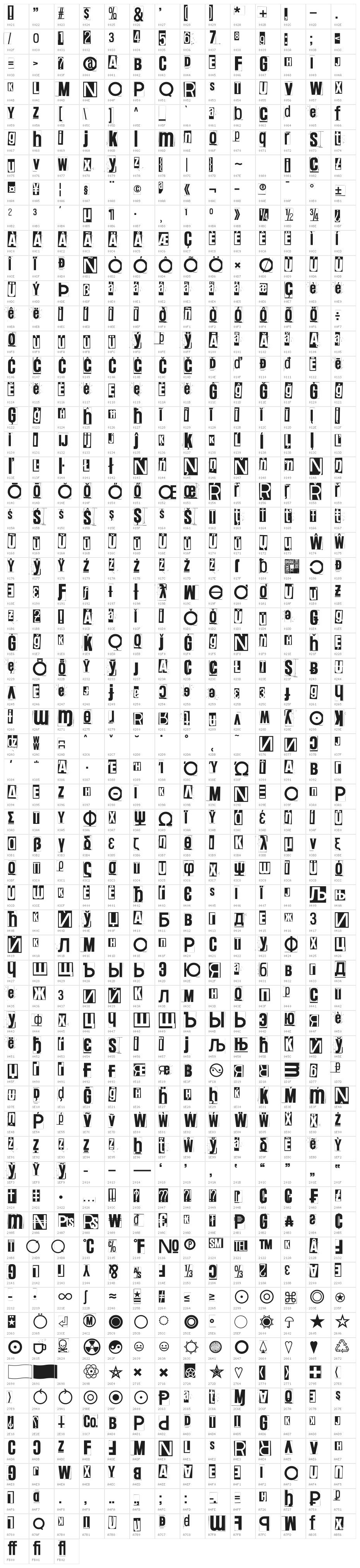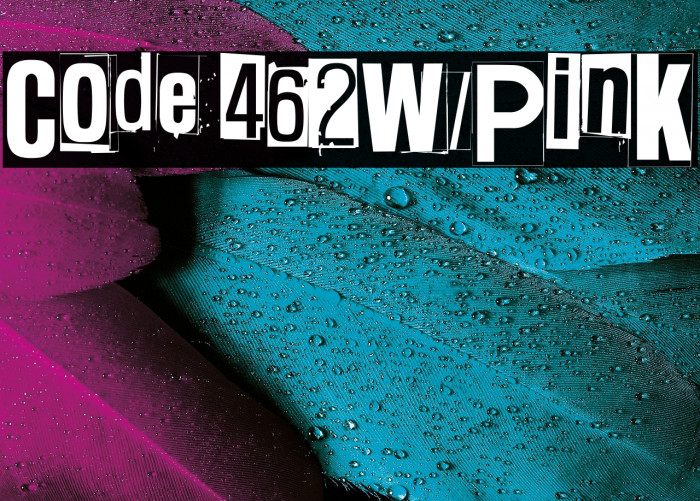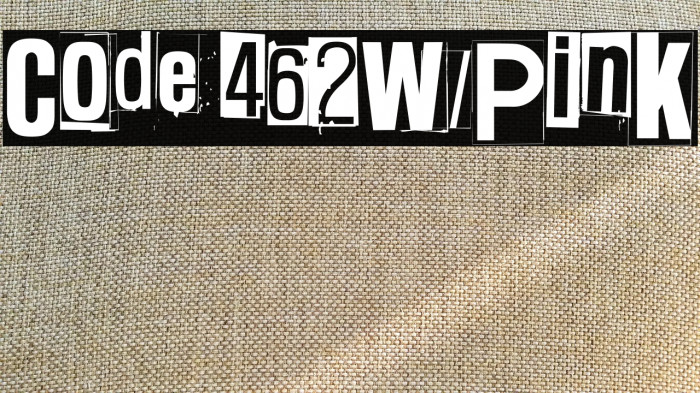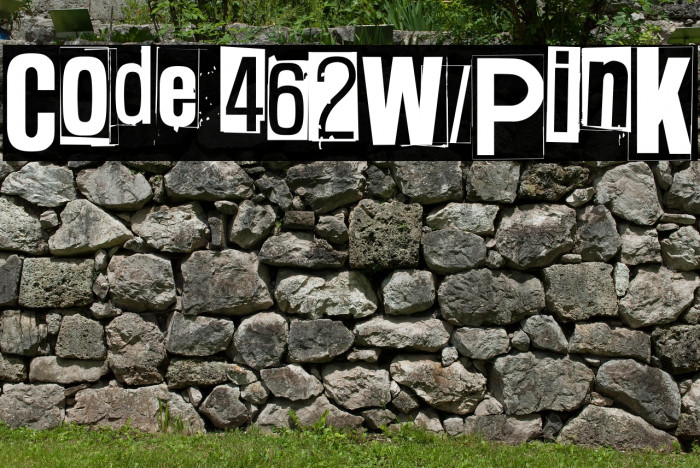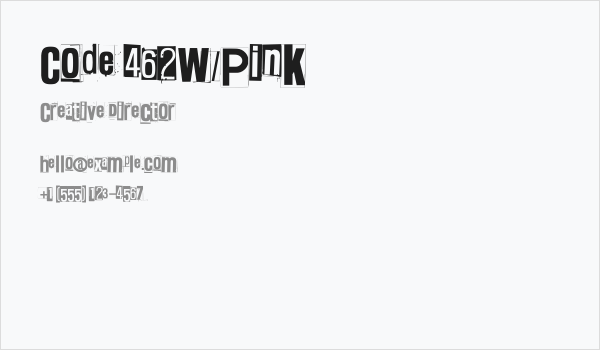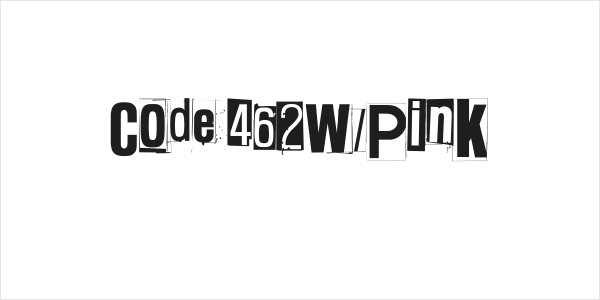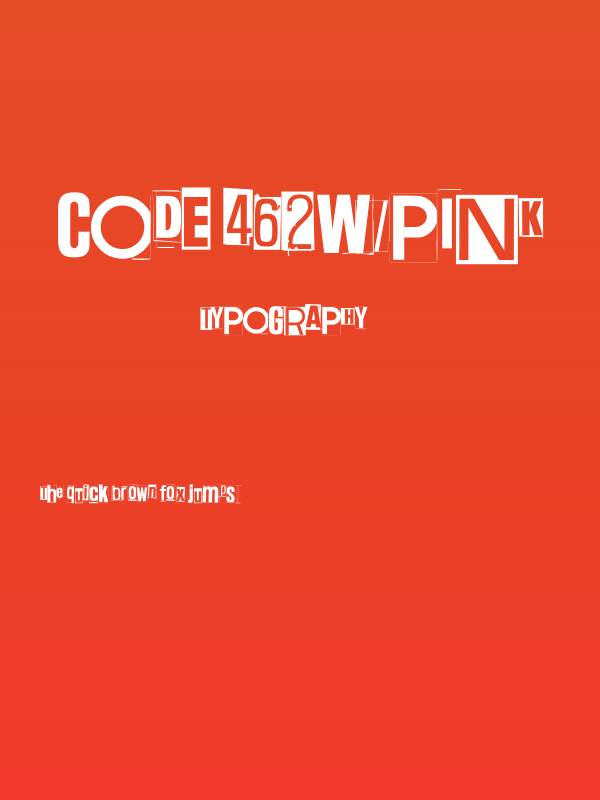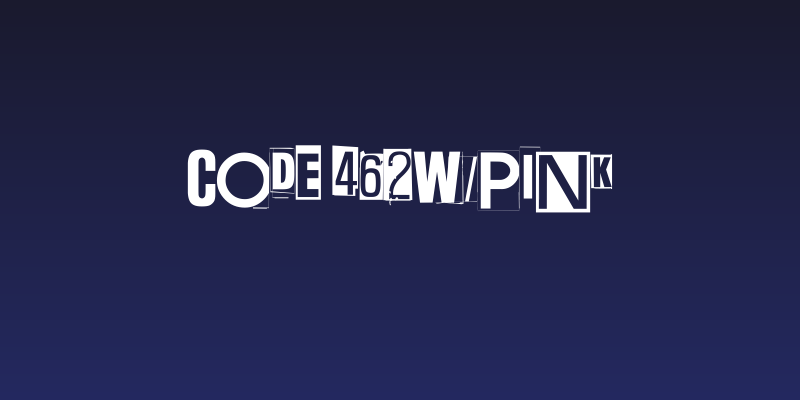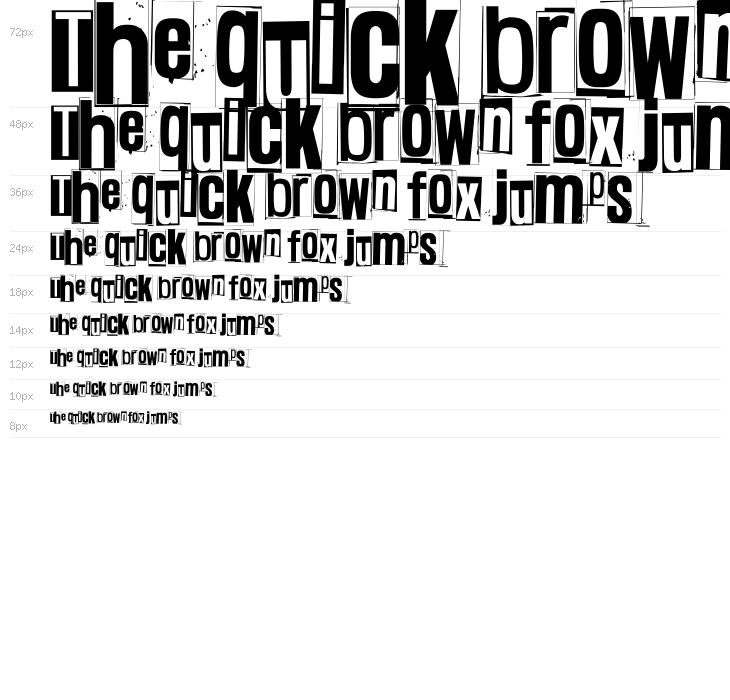
Code 462W/Pink Font
| Gesamtstil | Vintage, Artistic |
| Anwendungsfall | Headlines, Artistic projects, Posters |
| Vorgeschlagene Projekte | Ideal for posters, album covers, artistic projects, and any design requiring a bold, vintage look. |